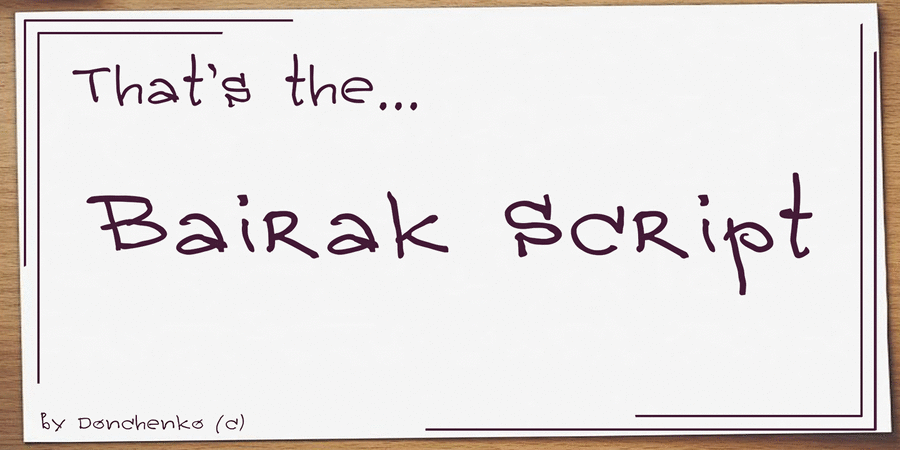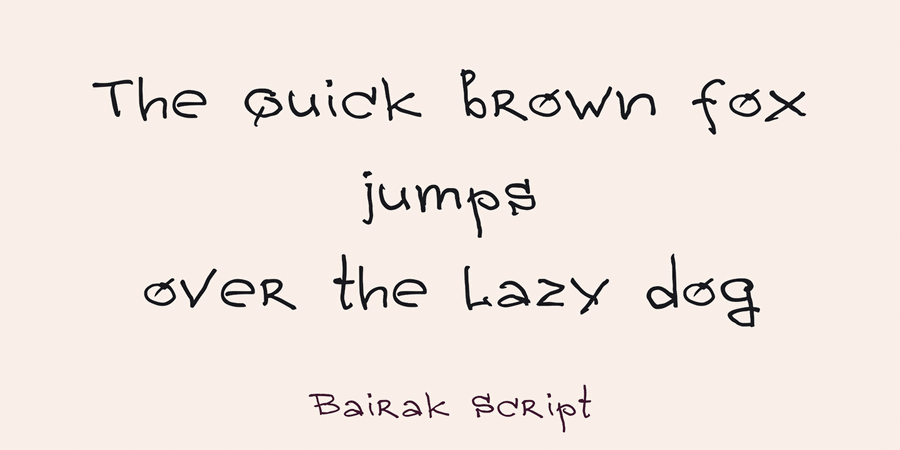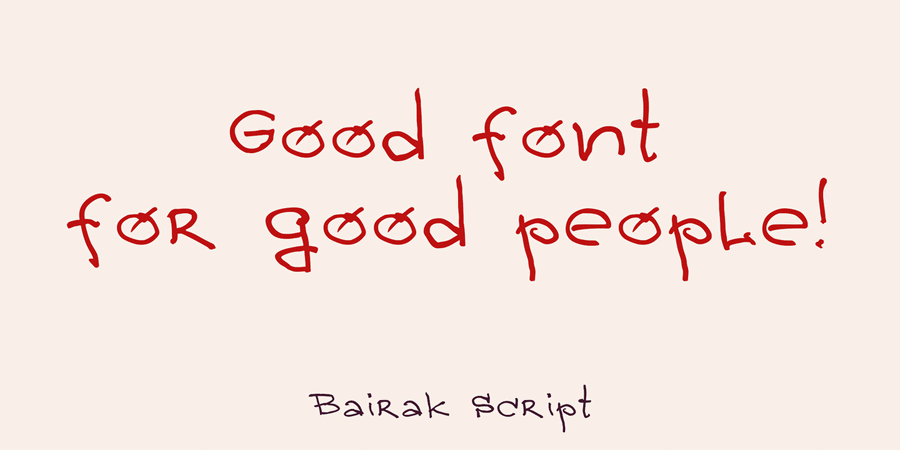
Цей шрифт створено на основі почерку відомого українського барда та художника Віктора Байрака.
Bairak Script був розроблений Олександром Донченком у 2023 році.
комікс, листівка, щоденник, лист, зошит, шкільна дошка, автограф, мем, мультфільм, анімація, стінгазета, стікер, наліпка Адаптованість гарнітури до носіїв:
Асоціації з сімейством шрифтів Bairak ScriptОсобистість і характер гарнітури:
енергійний, активний, лихий, неформальний, веселий, бадьорий, натуральний, живий, темпераментний, домашній, органічний, грайливий, непосидючий, емоційний, неслухняний, пустотливий, рухливий, цікавий, вільний, вольний, ризикований, задерикуватий, характерний, рукотворний, крафтовий, артізанальний, моторний, динамічний, неохайний, жартівливий, вернакулярний, розмашистий, швидкий, гострий, колючий, шорсткий, дикий, перчений, легковажний, смішний, карикатурний, недбалий, оригінальний, сміливий, творчий, позитивний, потішний, радісний, побутовий, нервовий